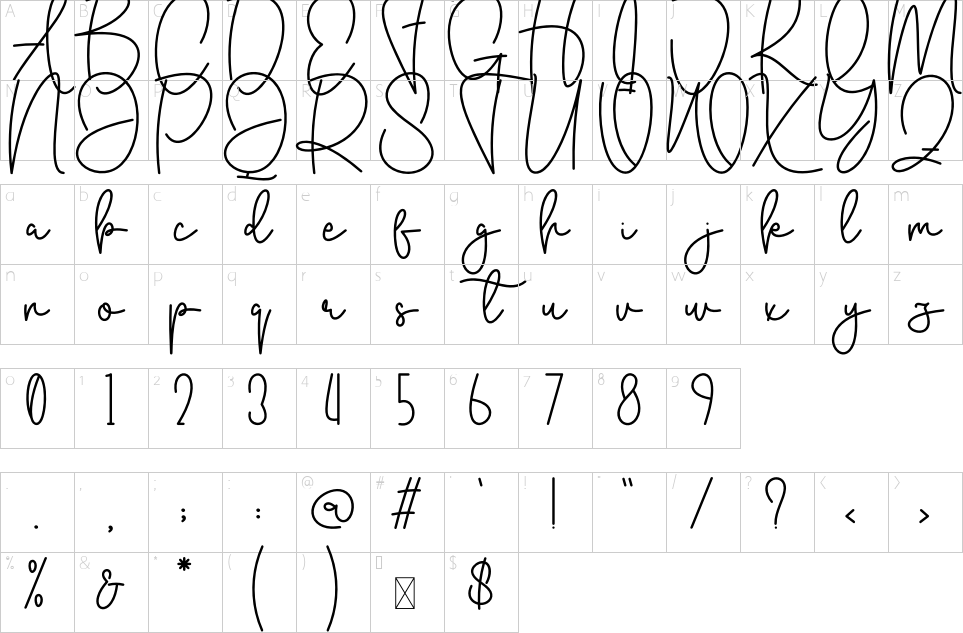
Descubra a elegância e a sofisticação da Jewerly Handscript, uma fonte gráfica delicada e romântica. Desenhada por scratchones, essa fonte gráfica livre é perfeita para designers de blogs, publicações de moda ou até mesmo para aqueles que adoram um toque delicado em seus trabalhos de arte digital. Se você busca uma fonte que combine elegância com um toque romântico, não pode deixar de experimentar a Jewerly Handscript. Ela tem sido baixada 317 vezes e não é difícil de entender por que. Sua letra fluida e curvilínea se adapta perfeitamente a qualquer tipo de projeto, tornando-a uma escolha versátil e incrivelmente atraente. Descubra por si mesmo o encanto da Jewerly Handscript.